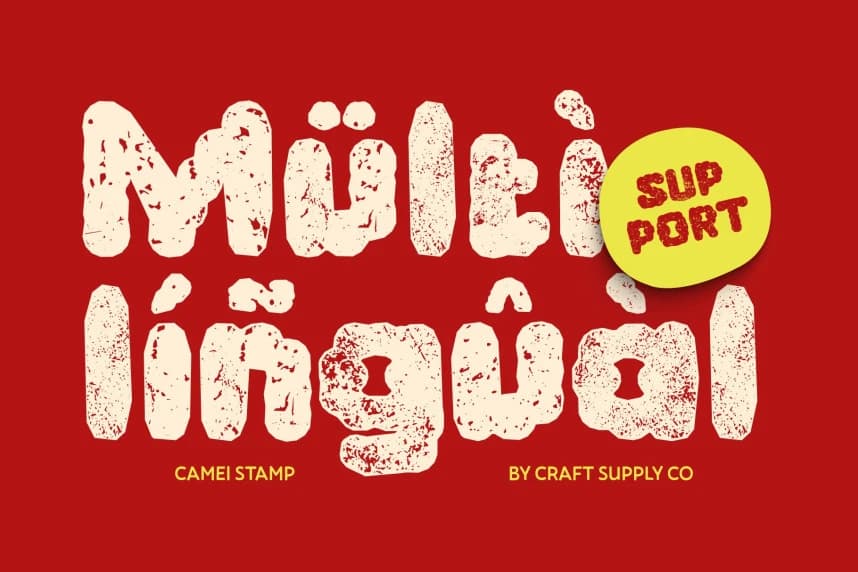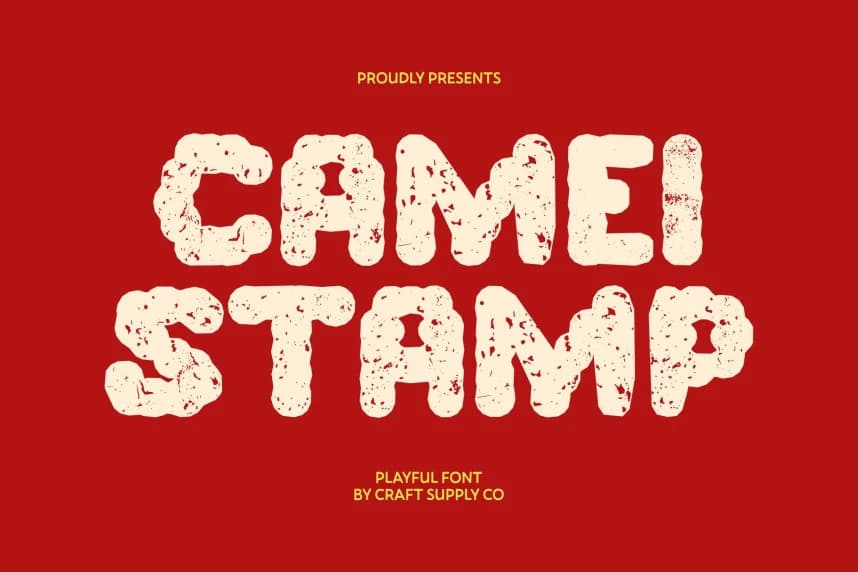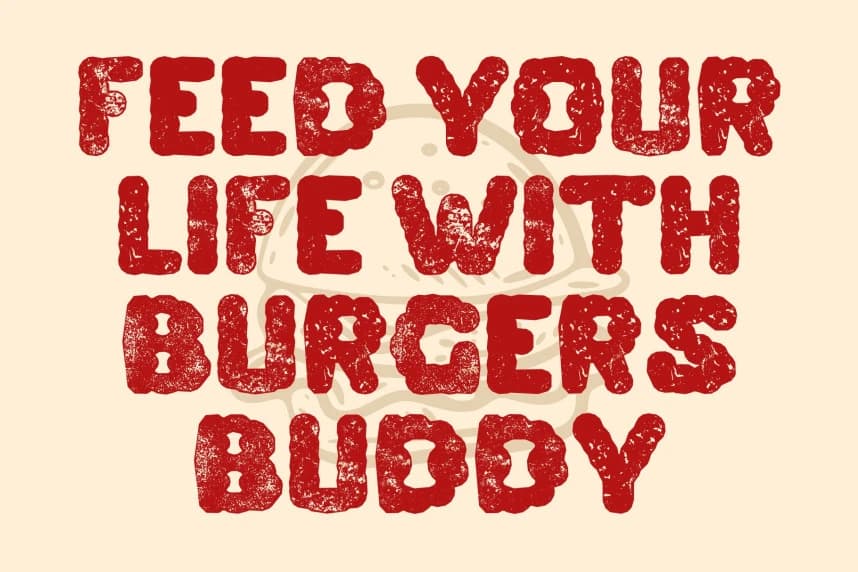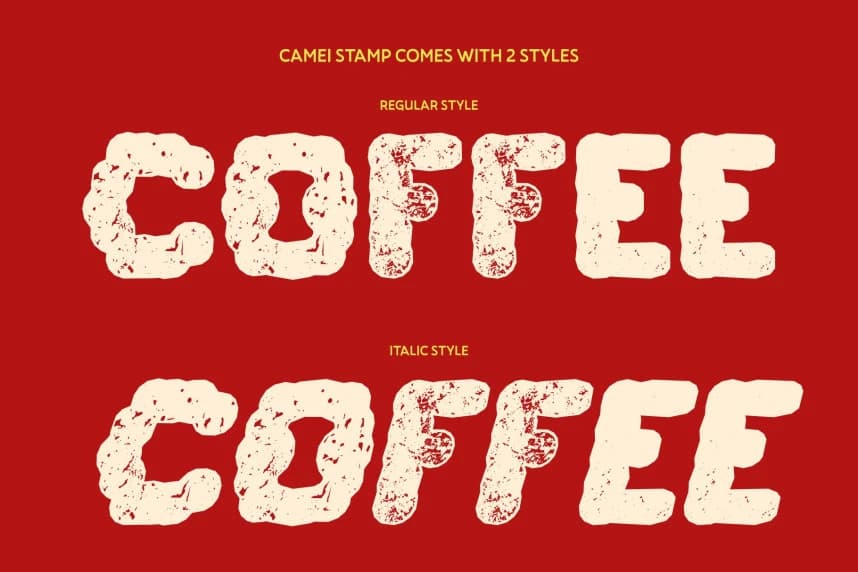
Camei Stamp Font – Bubble Font, Playful Vintage Texture ile Neşeli Bubble Stili ve Damgalı Karakterler. Bu, ince damgalı bir doku ile zenginleştirilmiş sevimli ve havalı bir Bubble display fontudur.
Camei Stamp Font – Bubble Font, Keyifli Vintage Doku ile Neşeli Kabarcık Stili ve Damgalı Karakter. Bu, ince damgalı doku ile güçlendirilmiş sevimli ve sıradışı bir kabarcık gösterim fontudur.